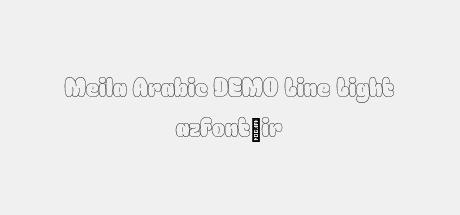
Meila Arabic DEMO Line Light
فونت زیبای رایگان Meila Arabic DEMO Line Light
قلم زیبای Meila Arabic DEMO Line Light از سری قلم های بسیار زیبا برای تایپوگرافی و لوگو تایپ می باشد.این قلم در وزن Regular و توسط Nasrullah Mehr, Zeeshan Nasar طراحی و منتشر شده است.